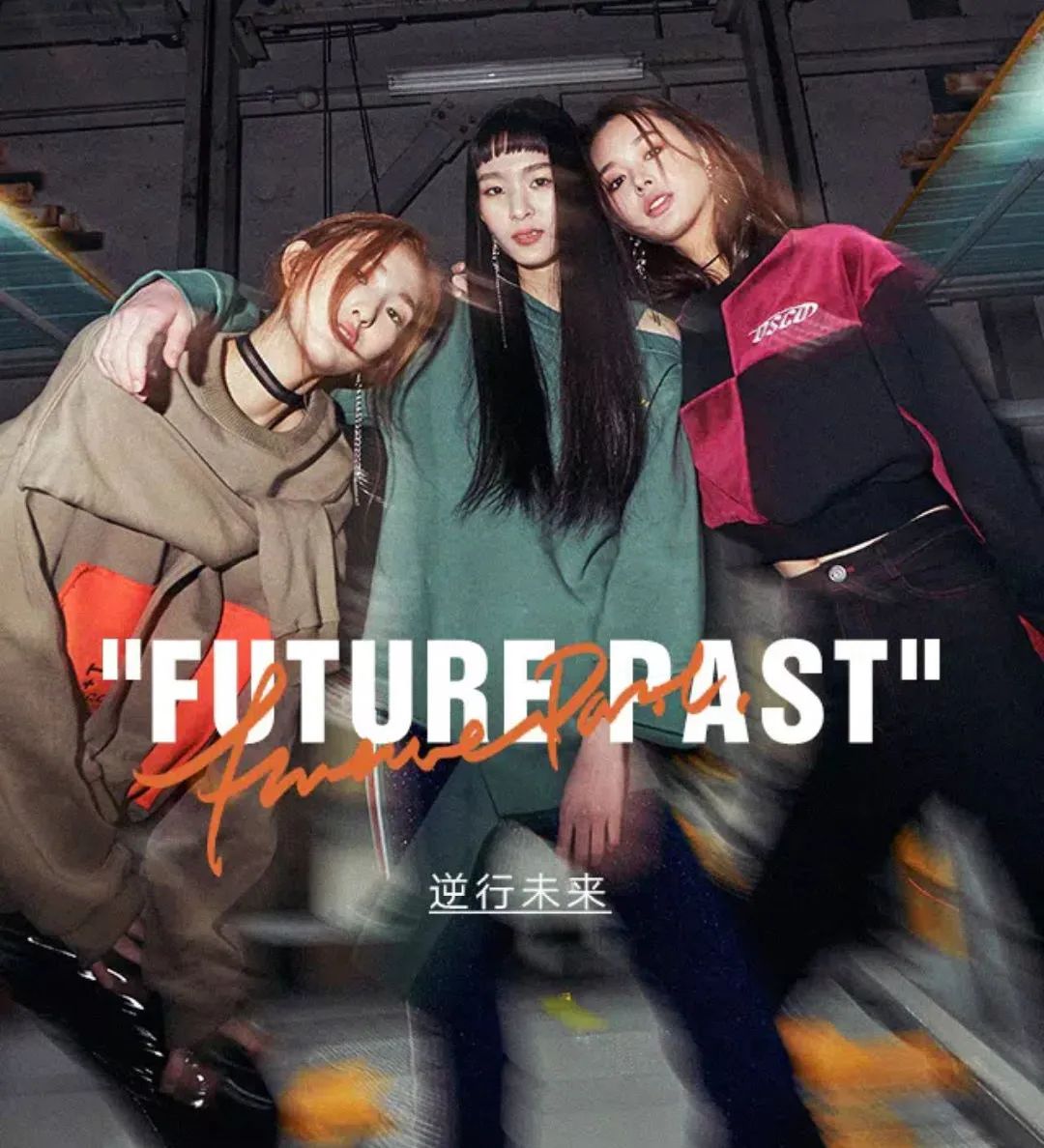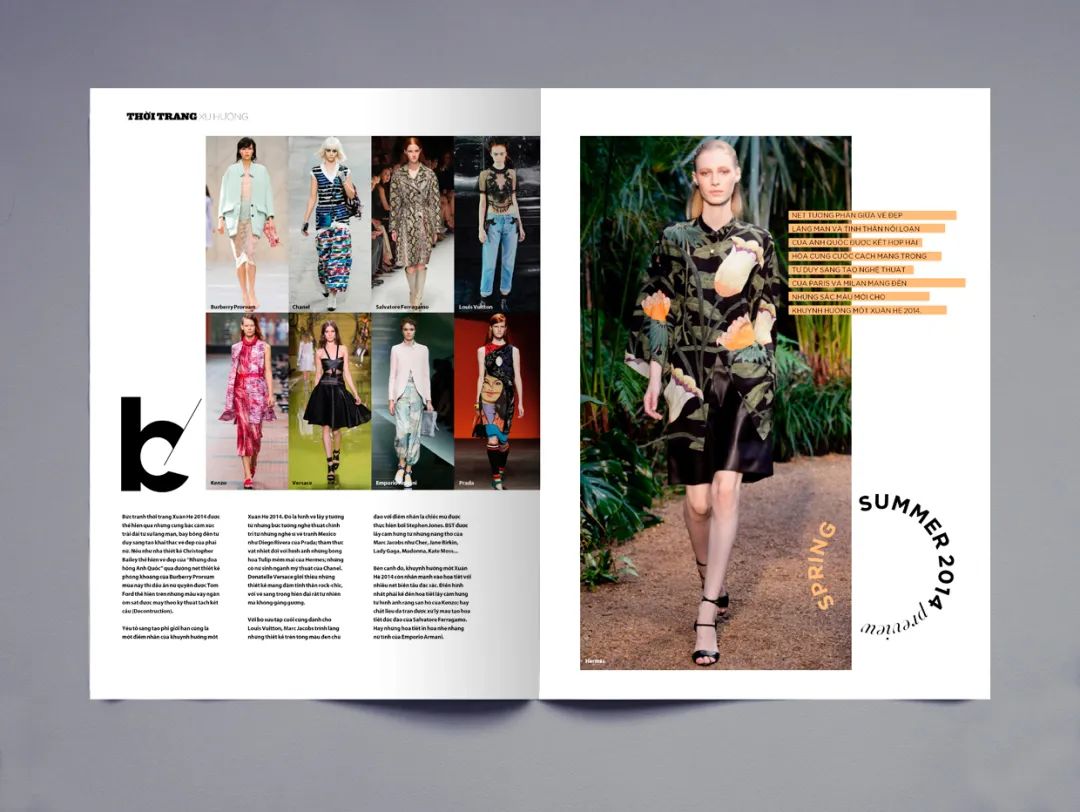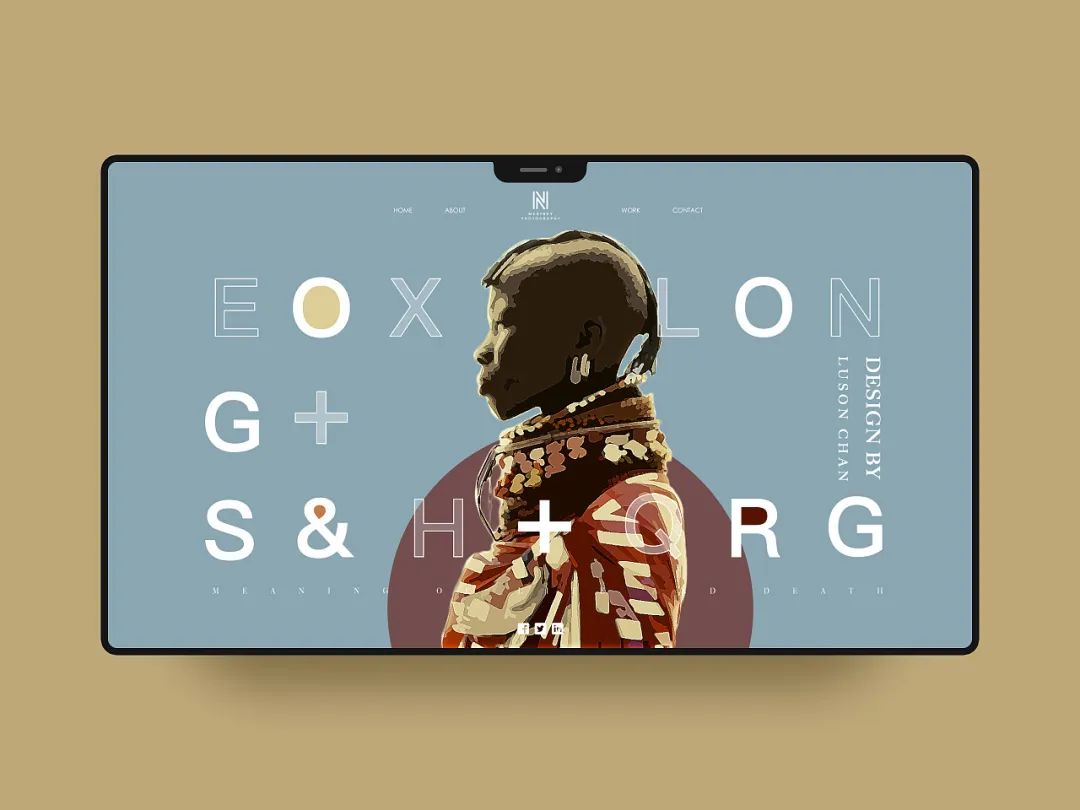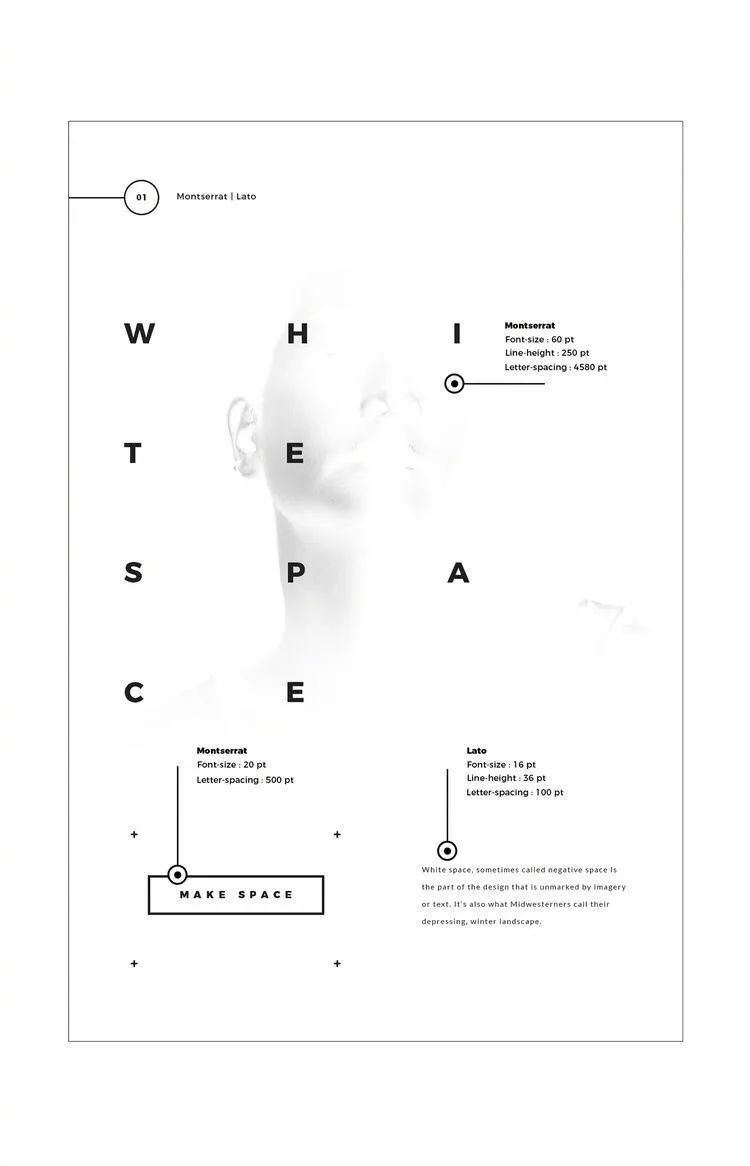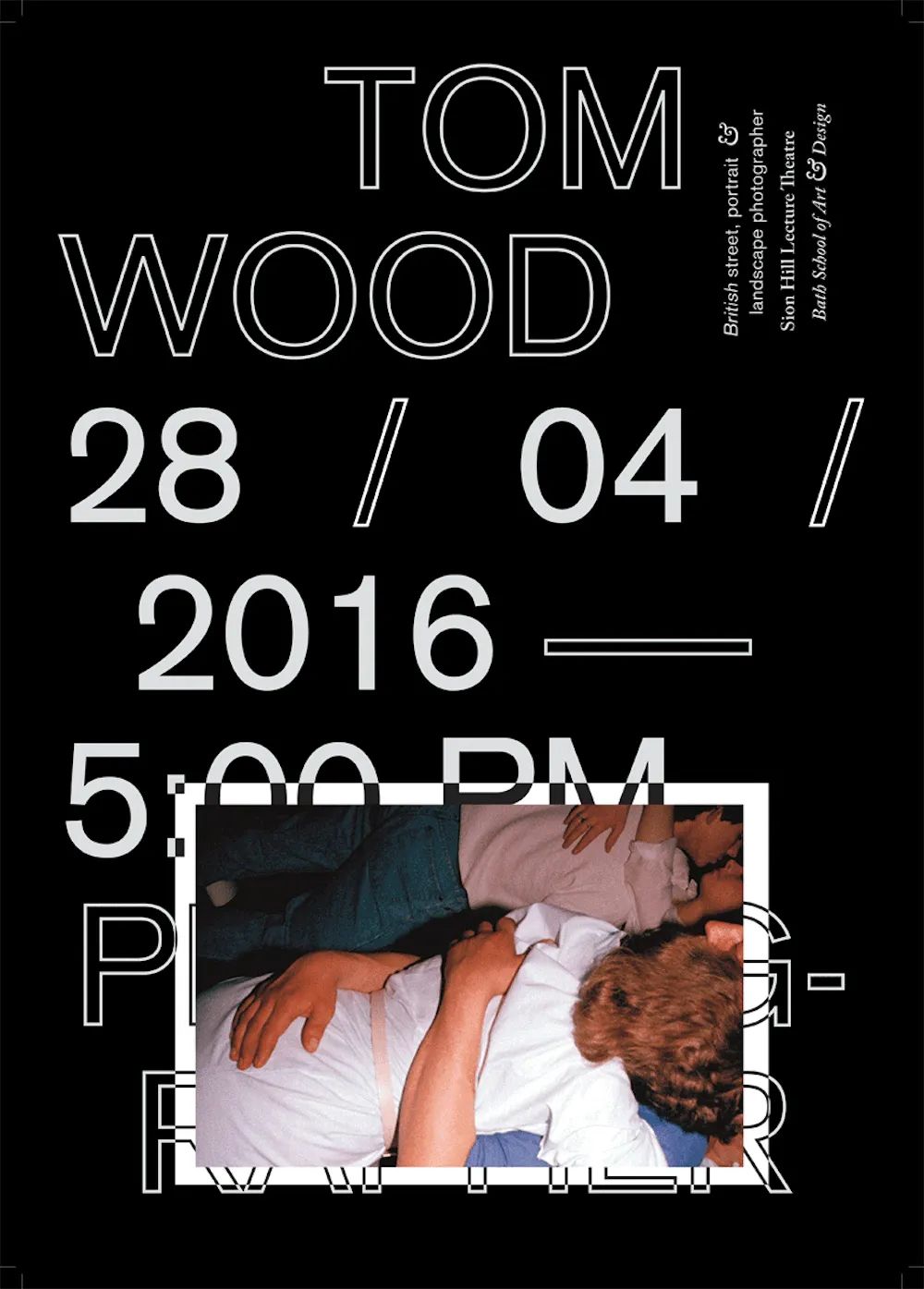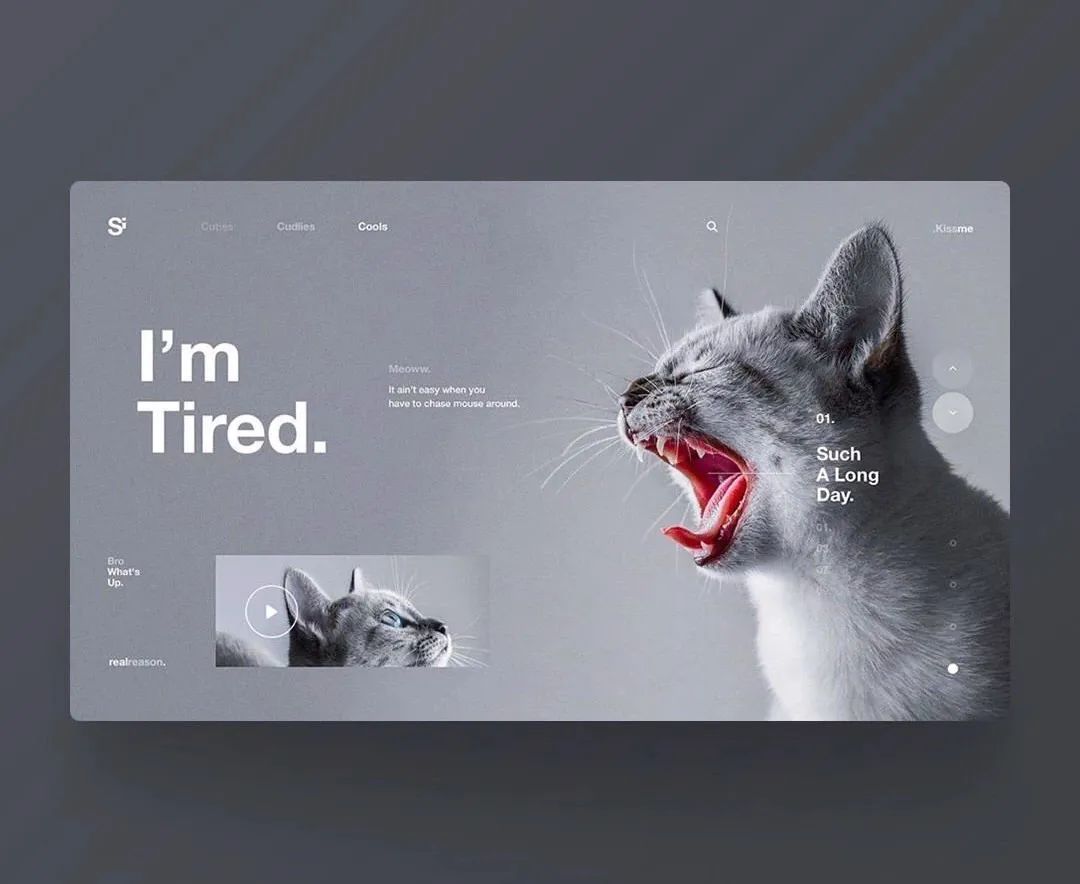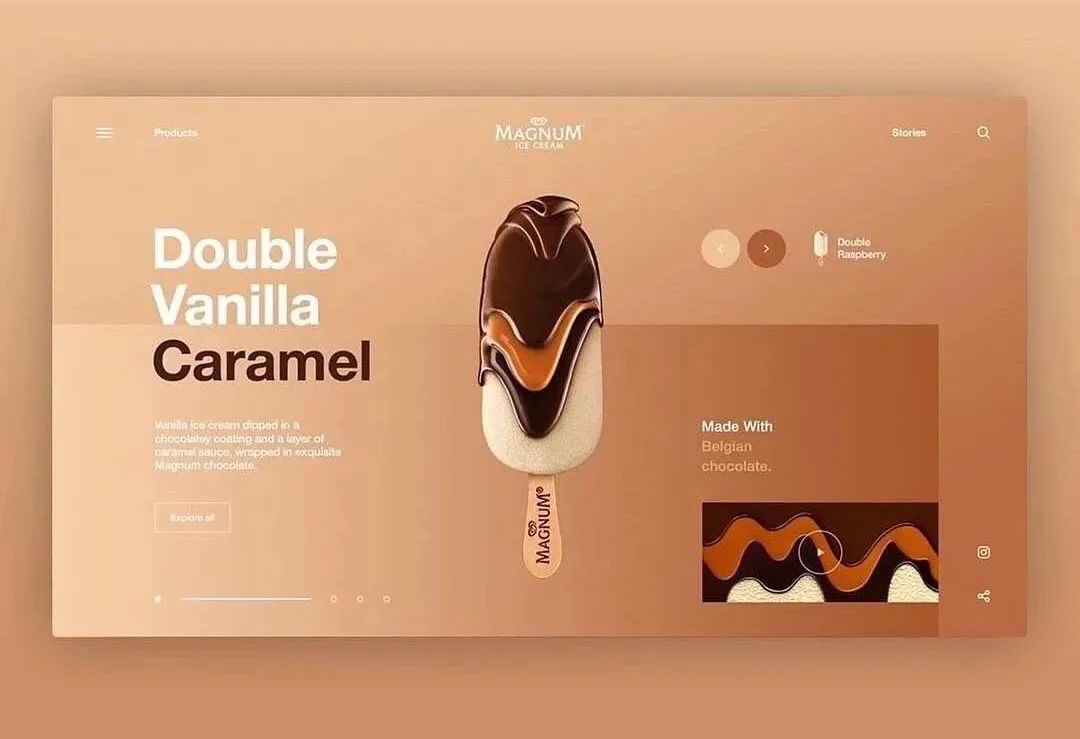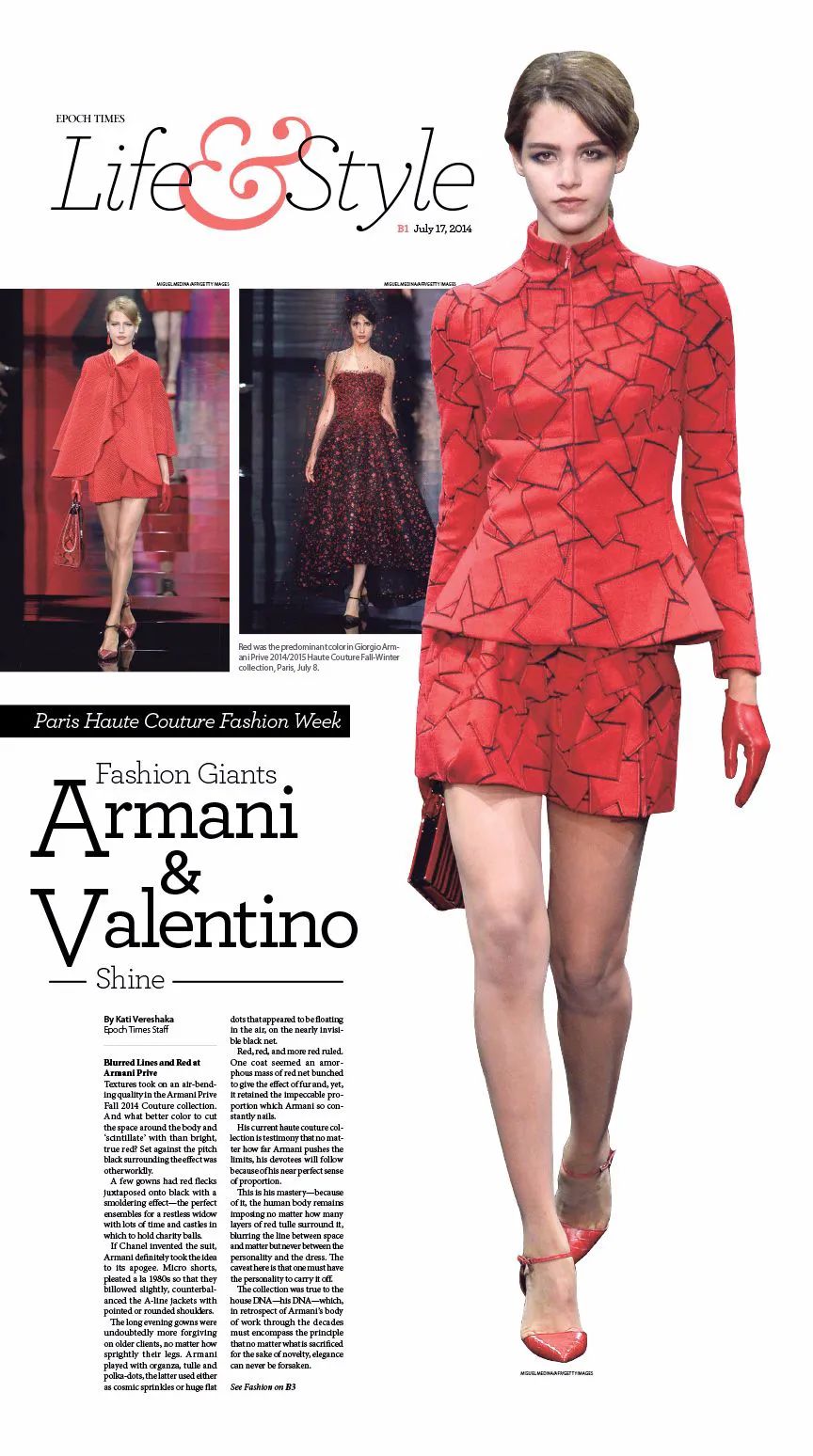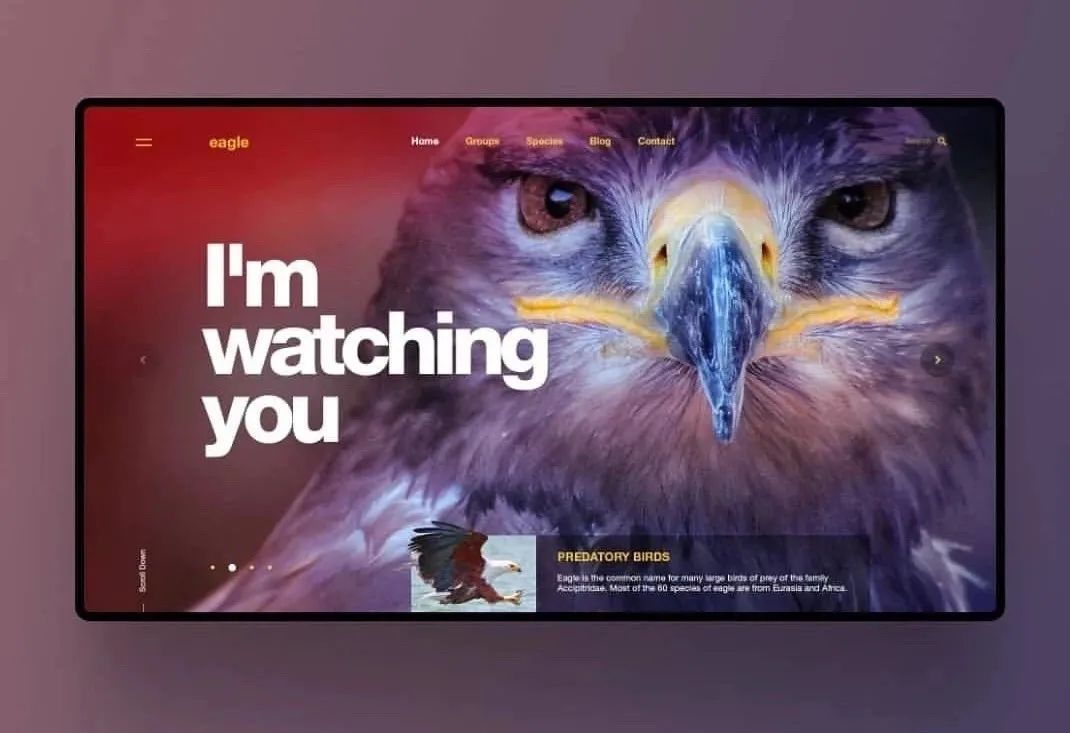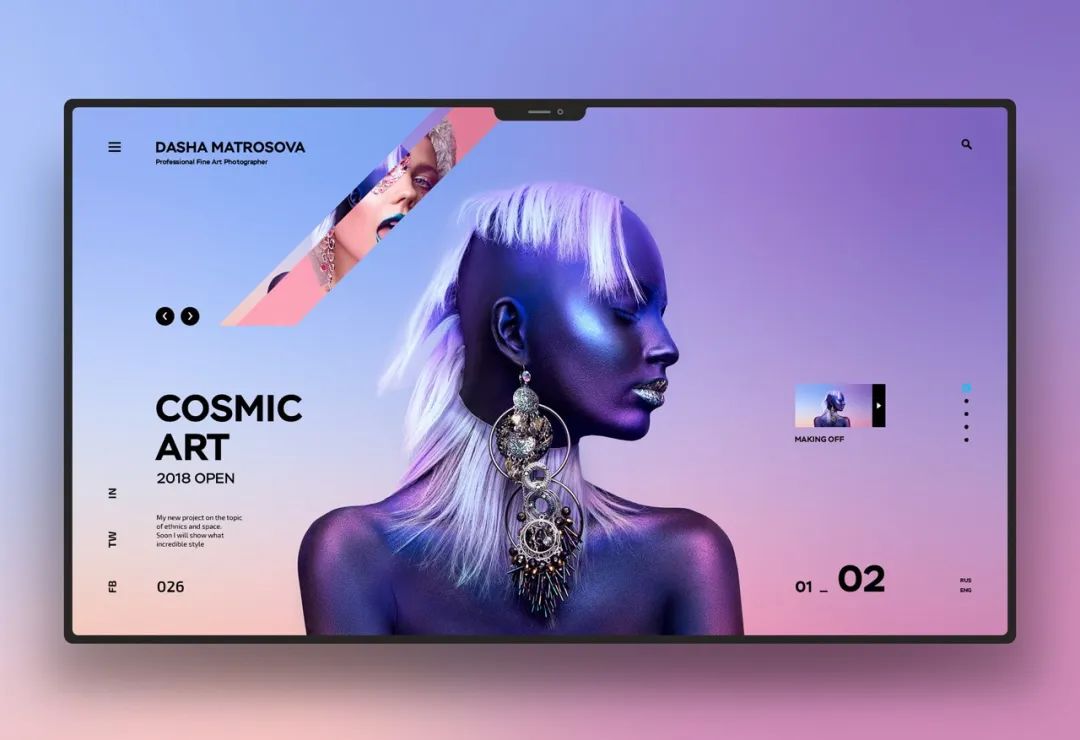
快速提升设计气质的7个版式技巧
排版的技巧有很多,而且随着设计的发展,每过一段时间都会有一些新的技巧流行起来,葱爷今天要给大家分享的这7个技巧,也是近几年比较流行,且容易上手、容易出效果的排版技巧。比如给英文或者中文标题选择一个笔画很粗的无衬线字体,然后在它上面加一个或几个比较潦草、笔画较细的手写英文单词,就能得到一个很不错的效果。
由于识别性不高,手写的英文单词最好是无关紧要的,主要是为了起装饰作用。
在此基础上还可以进行色彩搭配,而且颜色对比最好要鲜明一点,这样就建立起了强烈的粗细对比、大小对比、刚柔对比、色彩对比等。适合在海报设计、画册设计、网页设计中使用。
你是不是常常发现自己设计好的版面太过规矩,或者有点空、缺乏细节?而增加一个用英文排成的圆圈就可以解决很多类似的问题。
因为这个圆圈文字能与版面中的图片以及其他文字块形成轮廓对比、面和线的对比、曲和直的对比等。为了让其不太孤立和单调,最好最好把它叠加在图片或其他文字上面。组成圆圈的文字字体可以是衬线体、无衬线体或者手写体,但字号不宜太大,精致、秀气一点比较好看。
在正常的排版中我们都知道,字间距和行距都不能太大,而且间距要比行距小,而在文字比较少、版面比较空的情况下,我们可以把一些不是很重要且字数比较少的文字,采用大间距、大行距的方式排版。
这么做等于是把单词或者句子拆成了整齐排列的一组“点”,这样它就能与版面的其它元素形成点、线、面的对比,可以增强版面的设计感,而且能覆盖比较大的空间,起到装饰的作用。
这是类似于摄影中双重曝光的技巧,只不过把外轮廓图形换成了文字,所以这既是一个排版技巧,也是一种设计形式。为了效果比较好,用于填充图片的文字通常是字号较大、笔画较粗、字数较少的标题文字,图片也要选择质感好、颜值高的,如果是具象的图片则要尽量保证重要部分的完整性和识别性。
不是说要把文字做立体字,而是把文字按照一定的结构进行组合,或者把文字变形处理,从而达到三维效果。由于文字常见的状态是扁平的,所以当打破文字这种常规的状态,将其图形化、赋予三维效果时,就会具有很强烈的视觉冲击。在使用这一技巧时要注意文字的识别性。这一技巧同样也适用于标题排版,字体同样要选择笔画较粗的无衬线体,而且字号要大,描边字与无描边字的字号要统一或者比较接近。这种效果比较好的原因是,描边文字与无描边文字组合在一起,可创造出鲜明的线面对比、虚实对比、轻重对比。为了保证文字的识别性,文字的描边不要太细,也别太粗。在图片为人物、动物,或者产品的设计中,可以把最主要、或者质量最好的一张图片去底,并且拉大,然后再搭配1-2张比较小的方形图片,这样就能形成鲜明的大小对比和轮廓对比,效果也是不错的。
怎么样?以上的7个版式小技巧还不错吧,赶紧去试一试。你们可能也发现了,其实它们都是巧妙运用了设计中的对比原则,比如大小对比、粗细对比、点线面、平面与立体对比、轮廓对比、虚实对比等等。所以熟练掌握对比非常重要,你也可以在对比的基础上,尝试出很多有趣、好看的排版技巧和设计形式。